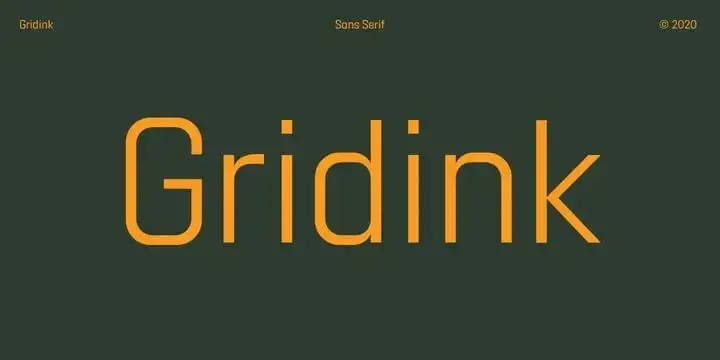
Gridink Sans Serif é uma fonte sem serílias que oferece uma mistura perfeita de poder e alegria para quem quer destacar sua escrita no ambiente digital ou impresso. Com um total de 9 pesos, 18 uprights (incluindo itálicos) e suas correspondentes itálicas, padrões e características únicas, você tem uma vasta gama de opções para personalizar seu design sem limites. Essa fonte foi projetada por Ckhans Fonts, um designer reconhecido no campo da criação de fontes, cuja proposta é permitir que as pessoas expressem a sua criatividade ao usar fontes poderosas e versáteis. Focadas em trazer uma experiência única para quem usa Gridink Sans Serif, essas características incluem suporte linguístico ampliado, fracionamento de números, figuras tabelares, símbolos e ligaduras únicas, bem como padrões interessantes que podem ser usados conforme necessário. Desenvolvida com um olhar voltado para as opções avançadas do OpenType, Gridink Sans Serif oferece uma abordagem moderna e versátil ao seu design, permitindo que você encontre o equilíbrio perfeito entre estilo e funcionalidade. Seja no layout de um site web ou no design de uma capa de livro impresso, acredite-se, Gridink Sans Serif será sua fonte favorita para levar seus projetos do papel ao topo.